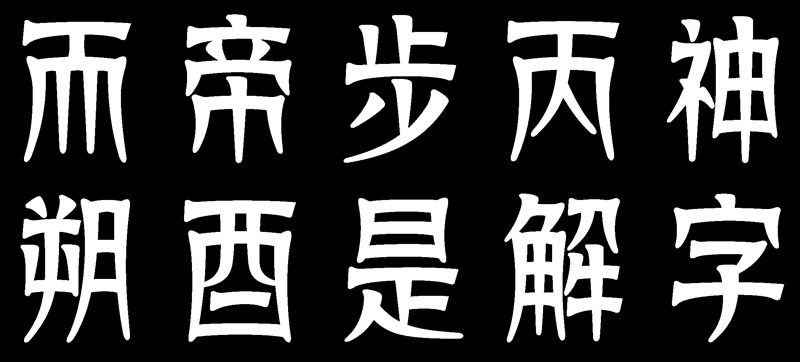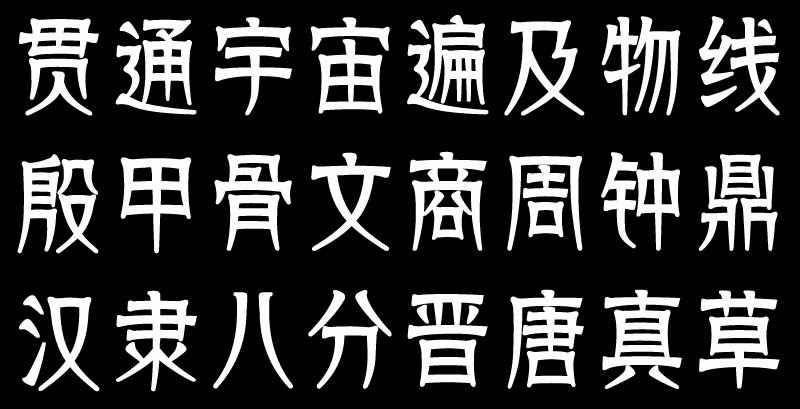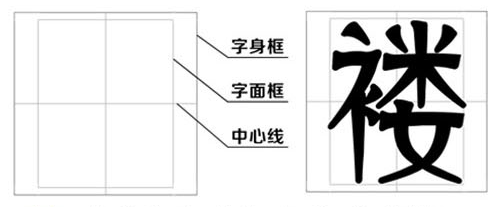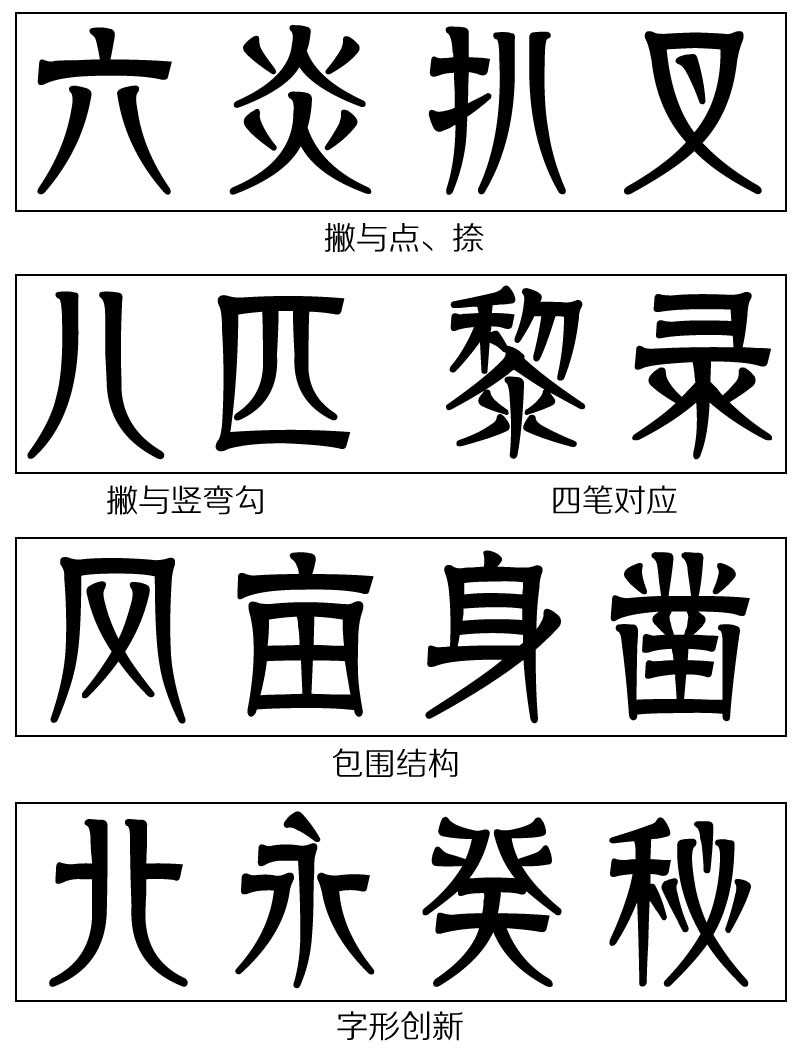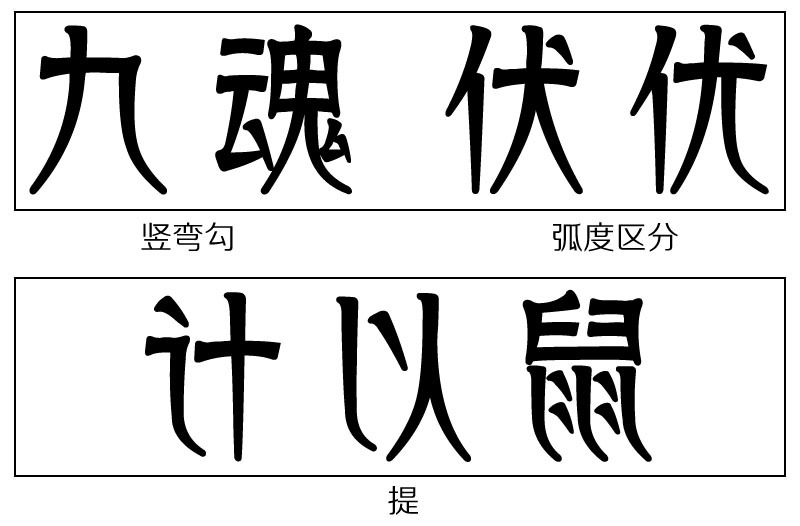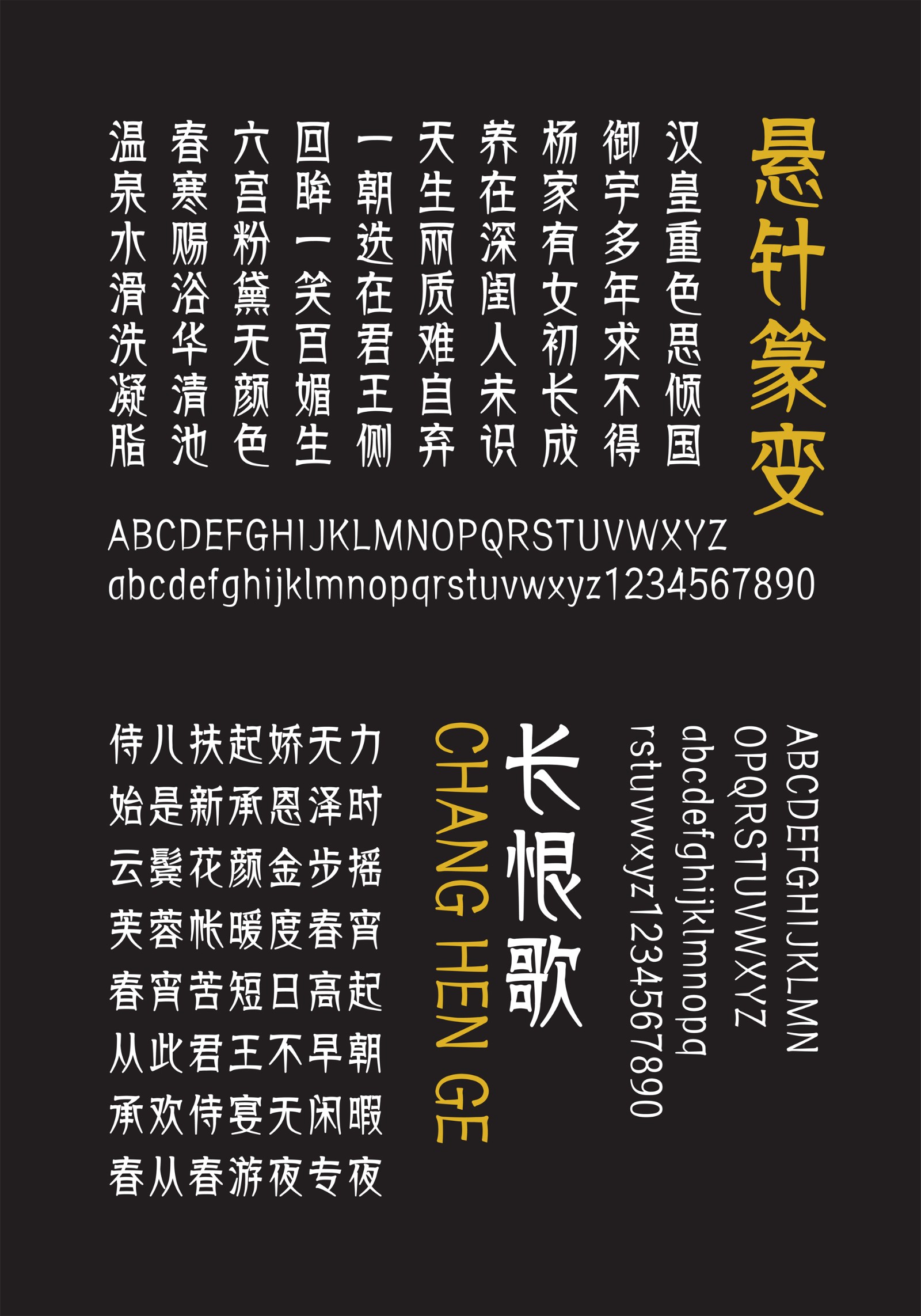
方正悬针篆变
字体品牌: 方正字库 设计师:卢帅 字体分类:创意字体 字体属性:精品字 字符集:大陆简体(GB2312-80) 发布时间: 2009
方正悬针篆变的创意源于三国东吴皇象所书的《天发神谶碑》。这款字体的字形保留了篆书悬垂、对称等规律,并将隶书与楷书的笔画特征融为一体,实为三种书体的统一。整体字形修长,结构上密下疏,起笔见方,收笔尖锐,如钢针下悬。方正悬针篆变将传统书法艺术融入现代字形之中,风格复古,装饰性强,适用于历史题材类的宣传设计,以及武侠类的影视、动漫和游戏。
悬针篆变设计阐述
起源:宋拓三国吴刻《天发神谶碑》(拓本半开纵32cm,横20.6cm,1956年家属捐赠故宫博物院藏)也叫《天玺纪功碑》、《吴孙皓纪功碑》,俗称《三段碑》,传为皇象所书。关于此碑的记载:公元264年,三国吴孙皓继帝位,由于他残暴昏庸,政局日益不稳。276年,改元天玺。为稳定人心,佯称天降神谶文的舆论以为吴国祥瑞。刻碑于一巨大的矮圆幢形石上,立于江宁(今南京)天禧寺。后碑石断为三截,故名《三截碑》。也有说此碑乃三石垒成,非是断裂。清嘉庆十年(1805年)三月,此碑毁于火灾。
《天发神谶碑》总体以秦隶之方,参周籀之圆。起笔见方而收笔尖锐,同时保持小篆结体上紧下松的整体格局。用笔方劲,横画、横折笔画、点、竖画起笔均用方笔,下笔处如刀斩斧截,竖画收笔多用悬针,像尖刀入地,别具一格。尖气构成了此碑的特异风格,故称作“悬针篆气”。加之垂直笔画有锋棱、似飘带,又称“韭叶篆”。康有为曾惊叹为“奇书惊世”,张叔未则云“吴《天玺纪功碑》雄奇变化,沉着痛快,如折古刀,如断古钗,为两汉来不可无一不能有二之第一佳迹”。后世篆刻家深受此碑启发,多取其笔意入印。赵之谦“丁文蔚”一印便有此意味,后世认为这方印启发了齐白石,从而形成大刀阔斧、斩钉截铁的齐派篆刻风格。
理念:《天发神谶碑》若篆若隶,转折方圆并用,将两者有机融合在一起,打破对篆书固有的定义。悬针篆变的设计灵感即缘于此,以隶体效篆书,留有篆书遗意。取其起笔方硬而收笔尖锐、结体上密下疏的特点,字型修长,有如钢针下悬。篆书繁复难读,做成简体字必须有大幅度的改造,不能只沿用原碑风格。定位为篆书变体,意在保留篆书韵味,如悬垂、对称及规律性,并将隶书与楷书笔画特征熔于一炉,实为三种书体的统一,创造出一种新的体式。同时增强“韭叶篆”的特点,将原碑文的刚猛风格做了纤秀柔美化的改进。将传统书法与现代形式语汇融合,追求飘逸柔美、开张疏朗、雍容大气的艺术美感,复古却易读。特征较为鲜明,适用于古典或玄幻风格的广告、书刊、影视及电脑游戏等用字。
初稿
二稿
终稿
结构:字形修长,重心偏上。
笔形:横画取隶书的蚕头燕尾,长横笔锋明显、收笔倾斜角度大,短横斜度小。
点、竖、撇、捺、提的起、收笔均一致,追求风格统一。
因字形修长,不适合参照隶书,故起笔取楷书笔意。
为体现悬垂特点,点、捺笔势倒置。
起笔及折肩是最大特征,曲线圆润饱满、左右对称,忌尖锐或粗钝。
点画:
为体现篆书悬垂的特点,将部分笔画变形做悬垂处理。
排版展示效果
应用效果
书籍封面应用
礼品包装应用
影视字幕应用
电视剧发布会现场应用